21 Font Untuk Tato dengan Gaya Terbaik Gratis
21 Font Untuk Tato dengan Gaya Terbaik Gratis – Ada sesuatu yang istimewa tentang jenis huruf dengan elemen yang digambar dengan tangan. Jenis gaya ini cenderung memiliki skrip atau nuansa yang lebih menyenangkan. Karena sifatnya yang lebih ringan, gaya yang digambar tangan ini tidak dapat membawa desain atau bekerja dalam situasi tampilan.
Di situlah tren tipe baru muncul sebagai font tato. Apa yang baik tentang tipografi gaya tato adalah bahwa mereka memiliki daya tarik yang sama dengan tulisan gambar tangan, tetapi sering kali lebih berani dengan goresan yang lebih tebal, menjadikannya pilihan yang kuat untuk tampilan huruf atau seni kata yang di aplikasikan pada kulit.
Ketika Anda sedang mencari font untuk desain tato, Di sini, Anda akan menemukan koleksi 20 lebih font tato gratis, dan perhatikan bahwa tipografi ini berasal dari berbagai sumber. Inspirasi Font-font ini dipilih dengan sangat hati-hati dan sesuai dengan kebutuhan font untuk jenis huruf yang sering digunakan untuk tato dan font baru untuk tato yang lebih segar.
1. Angel Tears
Font Angel Tears memiliki gaya tato yang mirip tinta. Bentuk huruf memiliki garis tebal dan tipis bergantian yang diwarnai agar tampak seperti hampir dibuat sketsa. Font ini berkelas dan terlihat agak kasar pada saat bersamaan.
2. Angilla Tattoo
Angilla Tattoo adalah font skrip yang berat dengan sapuan yang bagus untuk menambahkan sesuatu yang istimewa pada tulisan. Jenis hurufnya rumit terlihat agak feminin dan sangat mudah dibaca. Font untuk tato ini termasuk huruf besar dan kecil serta tanda baca dan beberapa karakter khusus.
3. Beech
Beech adalah seperangkat karakter tebal dengan tepi bulat untuk huruf sederhana. Font untuk tato ini mencakup huruf besar dan kecil dan satu set angka, dan meskipun memiliki tampilan yang keren untuk kata-kata pendek, itu bisa lebih sulit untuk digunakan untuk blok teks yang lebih panjang.
4. Blackletter
Blackletter adalah font khusus untuk desain tato dengan tipe gaya nama yang sama. Letter ini menampilkan serif yang tajam, sapuan tebal, dan getaran kuno dengan sedikit sentuhan tradisional. Muncul dalam gaya biasa dan bayangan.
5. CM Tattoo Dragon
Jenis huruf yang diilhami dari poster film ini mencakup bentuk huruf yang menarik dalam gaya blok. Jenis huruf all-caps mencakup karakter alternatif dari setiap huruf dengan tinggi keseluruhan lebih pendek, tanpa desender. Font ini juga cocok untuk desain tato.
6. Crux
Crux mencakup koleksi simbol yang terinspirasi tato. Dalam set font ini sudah termasuk salib, hati, kunci dan banyak lagi. Font untuk tato akan membuat pilihan yang bagus untuk set ikon atau karakter sederhana di seluruh desain.
7. Cute Tattoo
Kemungkinan Anda tidak pernah menggunakan kata “cute” dan “tattoo” dalam napas yang sama, tetapi font ini akan mengubahnya. Cute Tattoo adalah stroke seragam sederhana, font tato garis tipis. Pesonanya yang sederhana menjadikannya pilihan yang menyenangkan dan modern.
8. Death in the Shadow
Death in the Shadow memiliki perasaan menyeramkan yang dapat meningkatkan proyek yang lebih gelap. Set font sudah termasuk huruf besar dan kecil dengan angka dan beberapa karakter tambahan.
9. Deliquente
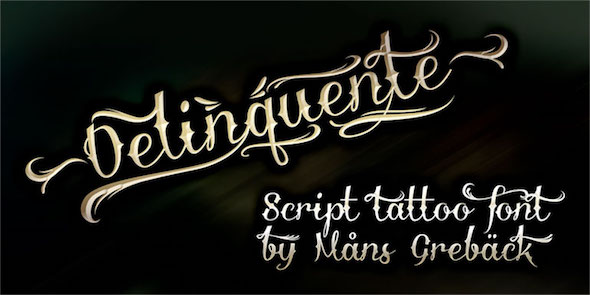
Deliquente memiliki tampilan yang hampir terinspirasi Barat tetapi dengan gaya yang lebih kasar. Font dengan banyak sapuan panjang dan ekor, bentuk huruf bergabung untuk menciptakan gaya kata visual yang menarik. Sementara karakternya rumit, mereka tetap dapat dibaca, dan kombinasi yang sangat baik.
10. Extra Ornamental No2
Extra Ornamental No2 adalah font huruf melengkung dengan banyak garis tipis di sekitar setiap huruf. Font yang rumit akan bagus untuk inisial atau big cap di tato, gunakan ide ini saat menampilkannya dalam proyek.
11. Ginga
Ginga adalah font gaya bercak tinta dengan ekor panjang dan swash menarik. Font tato itu mewah, tetapi tidak terlalu rumit untuk penggunaan sehari-hari untuk hampir semua jenis proyek yang membutuhkan tampilan huruf dengan pizzazz.
12. Ink in The Meat
Ketika Anda berpikir font tato, Ink in The Meat kemungkinan gaya yang terlintas dalam pikiran. Ini membawa kembali kenangan beberapa gaya tato lama yang populer di awal-awal diperkenalkannya seni tubuh. Jenisnya rumit dan berbasis skrip tetapi tangguh pada saat yang sama.
13. KR Blossoms 1
KR Blossoms 1 adalah kumpulan bentuk bunga sederhana dalam berbagai bentuk. Gunakan mesin terbang untuk ikonografi yang terinspirasi tato atau untuk aksen jenis huruf lain. Gaya dalam font ini memiliki varian yang cukup sehingga satu set dapat digunakan dalam banyak cara berbeda.
14. Ladylike BB Font
Jenis huruf gaya komik mungkin tidak langsung terlintas dalam pikiran ketika sedang memikirkan font untuk tato, tetapi menyenangkan untuk memiliki beberapa konsep yang lebih ringan untuk dipilih. Ladylike BB Font adalah gaya tulisan tangan kekanak-kanakan yang sangat mudah dibaca.
15. Loopy BRK
Loopy BRK adalah font tampilan menyenangkan yang memadukan huruf blok dan loop yang terinspirasi seni suku. Karakter dapat muncul sendiri, dalam loop dan dengan tutup ujung yang menawan.
16. Los Angeles
Los Angeles memiliki desain tato gaya biker yang menetapkan heboh di mana Anda hampir bisa mendengar deru mesin roda dua. Letter memiliki tepi tajam dicampur dengan kurva untuk bentuk huruf besar.
17. Original Gangsta
Original Gangsta membangkitkan kenangan sampul album hip-hop 1990-an dengan gaya swash-based yang nampak tangguh dan lembut pada saat bersamaan. Gaya itu disebut “badass” oleh satu komentator dan itu mungkin cara terbaik untuk menggambarkan jenis huruf ini dengan garis dan ekor yang rumit.
Baca : Cara Ganti Font di Bio Instagram Anda Jadi Lebih Menarik
18. Precious
Precious adalah font skrip tato yang rumit dengan banyak putaran dan swash di set huruf kapital. Bentuk huruf yang elegan memiliki sejumlah aplikasi dan dapat bekerja dengan indah untuk jenis tampilan pendek. Font ini dilengkapi dengan huruf besar dan kecil serta angka.
19. Serval
Serval adalah font untuk tato bergaya skrip dengan swash yang bagus dan kesan seperti kucing. Ini termasuk serif di garis dan tepi yang kasar. Huruf kecil memiliki tampilan kursif tradisional dengan gaya yang sama.
20. Shit Happens
Shit Happens adalah script menyenangkan yang memiliki banyak flair. Hampir setiap huruf tampaknya memiliki garis swash atau garis panjang yang membuat penggunaan font ini cukup menarik.
21. Tattoo Ink
Suka tampilan tato “MOM” tradisional? Ink Tattoo membantu Anda meniru gaya itu. Huruf tebal dicetak sebagian dari bawah ke atas. Font huruf besar semua termasuk dua varian dengan berbagai jenis isi dalam bentuk huruf – garis kecil dan segitiga.
22. Tribal Butterflies
Tribal Butterflies adalah set karakter font dan numerik yang mencakup berbagai serangga. Kupu-kupu bervariasi dari cahaya dan feminin ke elemen dengan garis yang lebih tebal dan nuansa seni yang lebih kesukuan.
23. Tribal Tattoo
Tribal Tattoo adalah font khusus untuk tato dengan banyak potongan seni yang terinspirasi gaya tribal. Set termasuk lingkaran, swash, bintang, bentuk binatang, tanaman, naga dan banyak lagi. Himpunan memiliki nuansa yang berbeda dan dengan goresan tebal untuk sebagian besar karakter, font tato ini memiliki semua mesin terbang yang Anda butuhkan untuk membuat sesuatu yang keren.